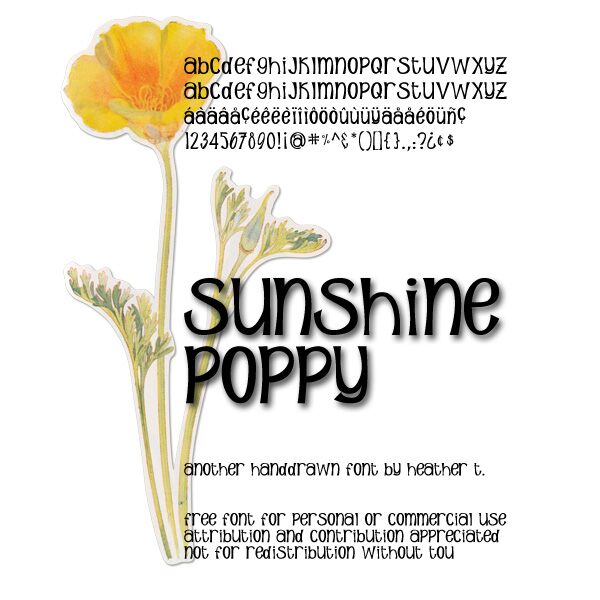
Sunshine Poppy, creata dalla talentuosa Heather Taylor, è un font display vivace. Il peso semi-light offre fascino e ottima leggibilità. Le curve giocose e il carattere estroso di Sunshine Poppy donano un'estetica fresca e coinvolgente. Il suo stile bilancia un'eleganza informale con un tocco creativo, rendendolo una scelta eccellente per branding, editoria e titoli d'impatto.
La versatilità di questo font gli permette di valorizzare diversi progetti grafici. Che si tratti di un invito divertente, di un poster dinamico o di un packaging innovativo, Sunshine Poppy aggiunge personalità a ogni tratto. Il peso semi-light garantisce leggibilità senza rinunciare alla vitalità del font. Sfrutta il potenziale creativo di Sunshine Poppy per infondere nel tuo prossimo progetto un'energia e uno stile inconfondibili.
Sunshine Poppy
Heather Taylor